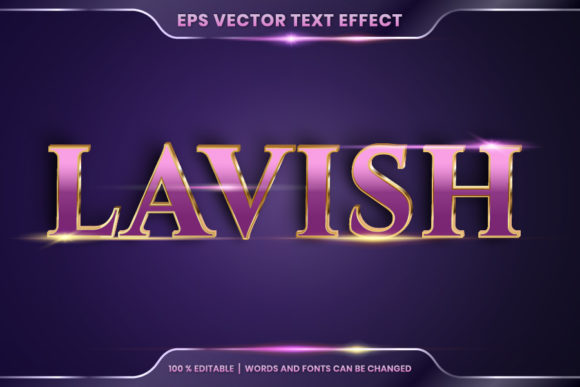
Text Effect in 3D Lavish Words
Jika anda sedang mencari aset berkualiti tinggi seperti Text Effect in 3D Lavish Words, pakej premium ini merupakan pilihan yang hebat untuk projek kreatif anda.
Sama ada anda mencipta produk POD (Print on Demand), jemputan perkahwinan atau grafik media sosial, Text Effect in 3D Lavish Words amat bersesuaian.